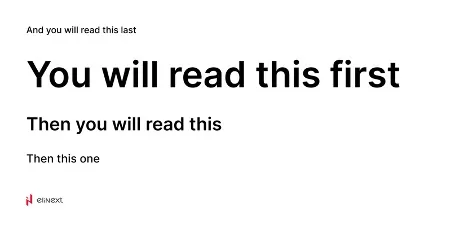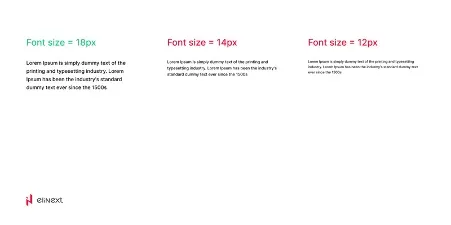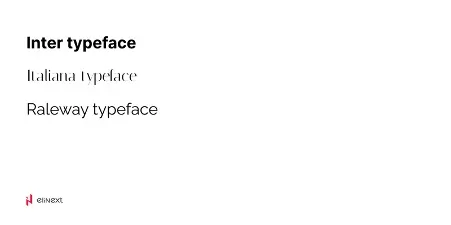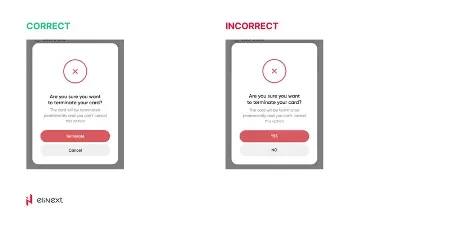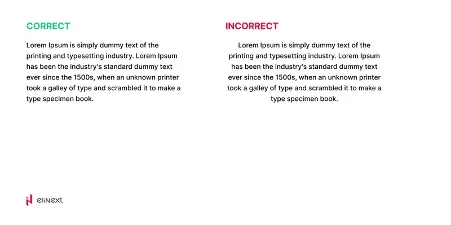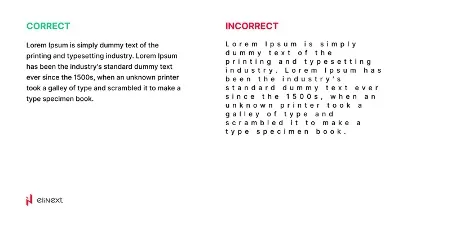
In diesem letzten Artikel der Reihe „Gestaltungsprinzipien“ wird die wichtige Rolle von Typografie und Farbe bei der Gestaltung erörtert.
Typografie umfasst die Auswahl und Anordnung von Schriften, um die Lesbarkeit zu verbessern und visuell ansprechende Designs zu erstellen. Dazu gehören die Auswahl der richtigen Schriftart, Schriftgröße, Abstände und Hierarchie. Auch die Auswahl und Verwendung von Farben ist entscheidend, um Emotionen zu wecken, eine visuelle Hierarchie zu schaffen und das Benutzererlebnis zu verbessern. Sowohl Typografie als auch Farbe sind wesentliche Elemente der Benutzeroberfläche (UI), über die Sie in diesem Artikel mehr erfahren: Gestaltpsychologie. Grundsätze Der Komposition Im UX/UI-Design.
Typografie
Typografie umfasst die ästhetischen und funktionalen Elemente der Textgestaltung unter Verwendung verschiedener Schriftarten, Symbole und Zeichen. Sie geht über die einfache Auswahl einer ansprechenden Schriftart hinaus, da ihr effektiver Einsatz das Benutzererlebnis, die Lesbarkeit, die Integration und die visuelle Organisation innerhalb eines Designs verbessern kann.
Hierarchie
Fast alle Schnittstellen enthalten irgendeine Form von Textinformationen. Die Umsetzung von Hierarchie in der Typografie trägt dazu bei, die Lesbarkeit einer Schnittstelle zu verbessern, so dass die Benutzer wichtige Informationen effizienter finden können.
Designer entscheiden sich für größeren und fetteren Text, um wichtige Informationen hervorzuheben, da dieser auf natürliche Weise die Aufmerksamkeit der Benutzer auf sich zieht. Kleinerer und leichterer Text eignet sich hingegen besser für weniger wichtige Inhalte.
Zeilenhöhe und Zeilenlänge
Die Einhaltung einer angemessenen Zeilenhöhe und -breite ist entscheidend für die Lesbarkeit von Text auf verschiedenen Gerätegrößen.
Die Zeilenhöhe bezieht sich auf den Abstand zwischen den Grundlinien der Textzeilen innerhalb eines Absatzes, der den Abstand zwischen den unsichtbaren Linien bestimmt, auf denen die Buchstaben zu ruhen scheinen. Die Zeilenlänge hingegen misst die Breite eines Textblocks und wird in der Regel in Zoll oder Punkt bzw. als Anzahl der Zeichen pro Zeile angegeben.
Zeilenhöhe
Um die Lesbarkeit und Zugänglichkeit zu gewährleisten, wird empfohlen, die Zeilenhöhe zwischen 130% und 180% der Schriftgröße festzulegen, je nach Textmenge. Größere Textblöcke erfordern also eine größere Zeilenhöhe.
In den Bereichen Design und Typografie ist die Berücksichtigung der Zeilenhöhe während des Schreibvorgangs von entscheidender Bedeutung, da sie die Lesbarkeit und den visuellen Reiz erheblich beeinflusst. Angemessene Abstände verbessern die Lesbarkeit und die Gesamtästhetik des Textes.
Zeilenlänge
Für eine optimale Lesbarkeit liegt die empfohlene Textlänge in der Regel zwischen 70 und 80 Zeichen. Innerhalb dieses Bereichs können die Benutzer eine ganze Zeile bequem lesen, indem sie einfach ihre Augen bewegen. Wenn eine Zeile jedoch mehr als 80 Zeichen umfasst, müssen die Benutzer möglicherweise ihren Kopf bewegen, um weiterzulesen. Diese Kopfbewegung kann dazu führen, dass das Verstehen des Textes schwieriger wird und der Benutzer frustriert ist, was letztlich zu einer höheren Wahrscheinlichkeit von Lesefehlern führt.
Lesbarkeit
Um sicherzustellen, dass die Typografie für Menschen mit Behinderungen wie Farbenblindheit, Seh- und Hörbehinderungen zugänglich und leicht lesbar ist, müssen die Web Content Accessibility Guidelines (WCAG) eingehalten werden.
Hier sind einige wichtige Tipps, die Sie beachten sollten:
1. Halten Sie eine Mindestschriftgröße von 16 px oder größer für allgemeinen Text ein und vermeiden Sie kleinere Größen wie 12 px bis 14 px für zusätzliche Informationen.
2. Achten Sie auf ein Farbkontrastverhältnis von mindestens 4,5:1 zwischen dem Text im Vordergrund und den Hintergrundfarben.
3. Halten Sie sich an ein gängiges Skalenverhältnis für Schriftgrößen, wie z. B. 1,250x, 1,414x, 1,5x und 1,618x, wobei jede nachfolgende Schriftgröße entsprechend dem angegebenen Verhältnis kleiner ist als die vorherige.
Anzahl der Schriftarten
Es ist ratsam, die Verwendung von Schriftarten oder -typen auf maximal drei innerhalb eines Projekts zu beschränken. Anstatt neue Schriftarten einzuführen, empfiehlt sich die Verwendung von Schriftfamilien. Schriftfamilien sind so konzipiert, dass sie sich gegenseitig ergänzen und so Flexibilität und Konsistenz auf der gesamten Benutzeroberfläche gewährleisten.
Darüber hinaus können bei vielen Projekten Probleme mit der Lesbarkeit durch die Verwendung einer einzigen Schriftart mit mehreren Schriftfamilien wirksam gelöst werden. Dieser Ansatz sorgt für eine kohärente visuelle Ästhetik und erfüllt gleichzeitig die Anforderungen an die Lesbarkeit.
Hier ein Beispiel für die Verwendung einer einzigen Schriftart mit mehreren Schriftfamilien: